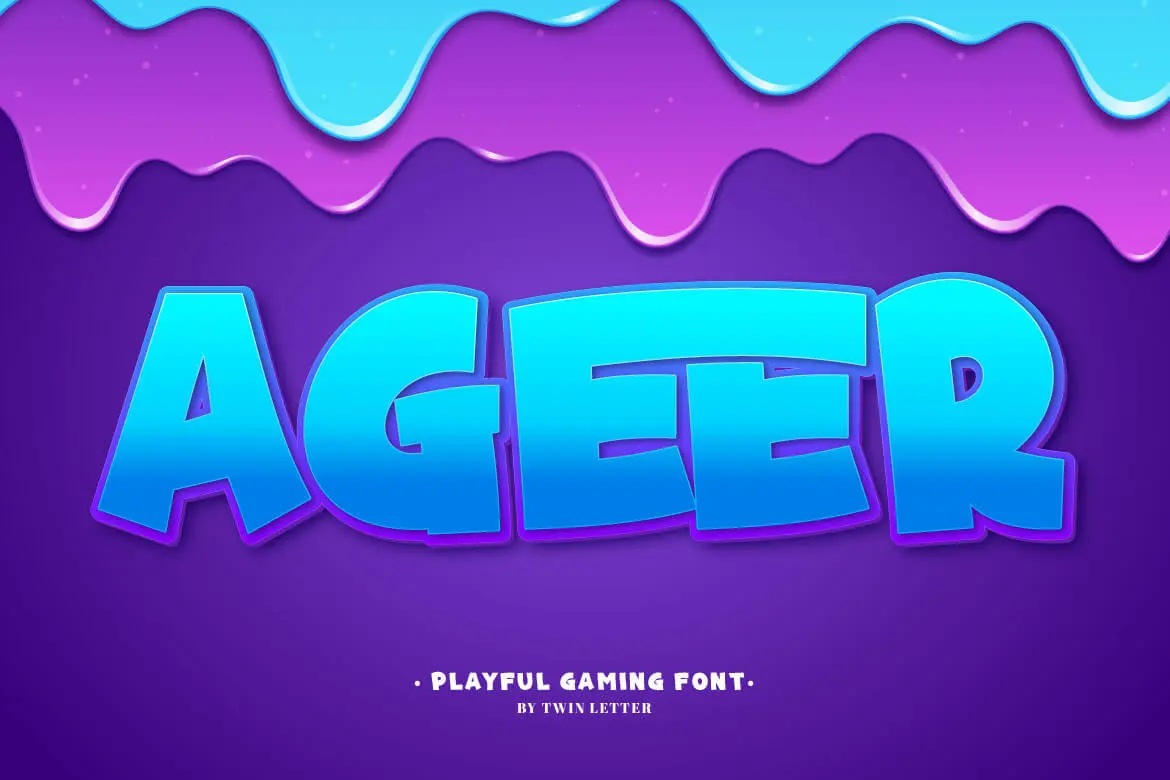
A Ageer Font é uma tipografia alegre e tranquilizadora com um tema encantador. Seu tom relaxado permite que você use essa fonte em diversos projetos para melhorar a aparência de suas criações, tornando-as mais belas e elegantes. Este tipo de letra é ideal tanto para design gráfico quanto para publicidade, garantindo uma presença visual impecável. Twinletter, o designer desta fonte, criou um elemento visual que traz tranquilidade aos projetos, ajudando a criar ambientes de trabalho mais confortáveis e relaxados. Perfeita para aqueles momentos em que você deseja adicionar um toque de simplicidade e beleza ao seu design, Ageer Font é uma ótima opção para qualquer designer gráfico. Com sua elegância e descontração, essa fonte se destaca como uma alternativa perfeita para quem procura algo leve mas poderoso no estilo do display typeface.